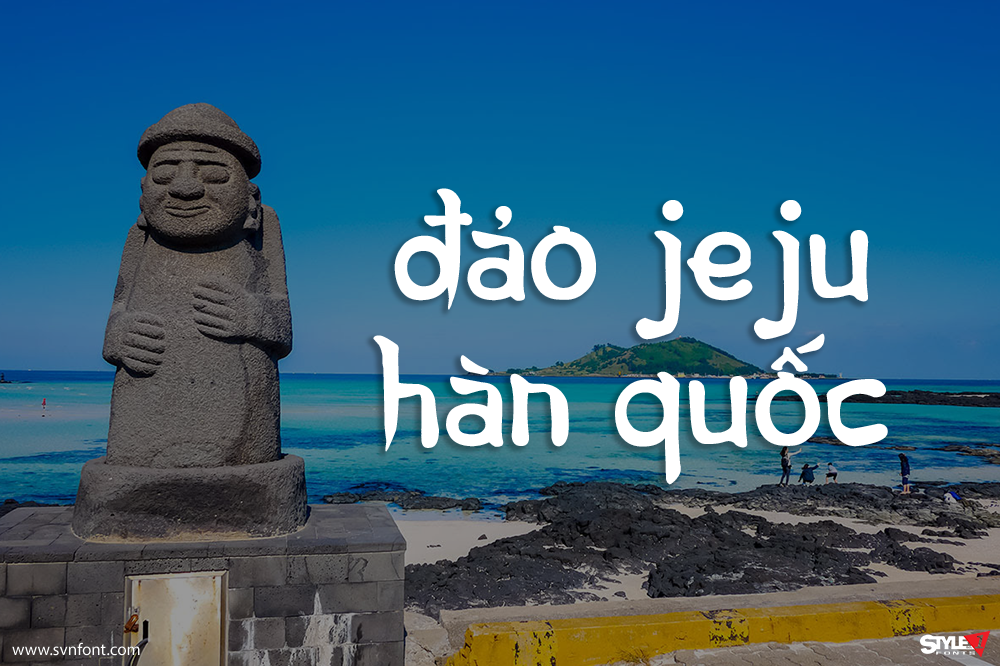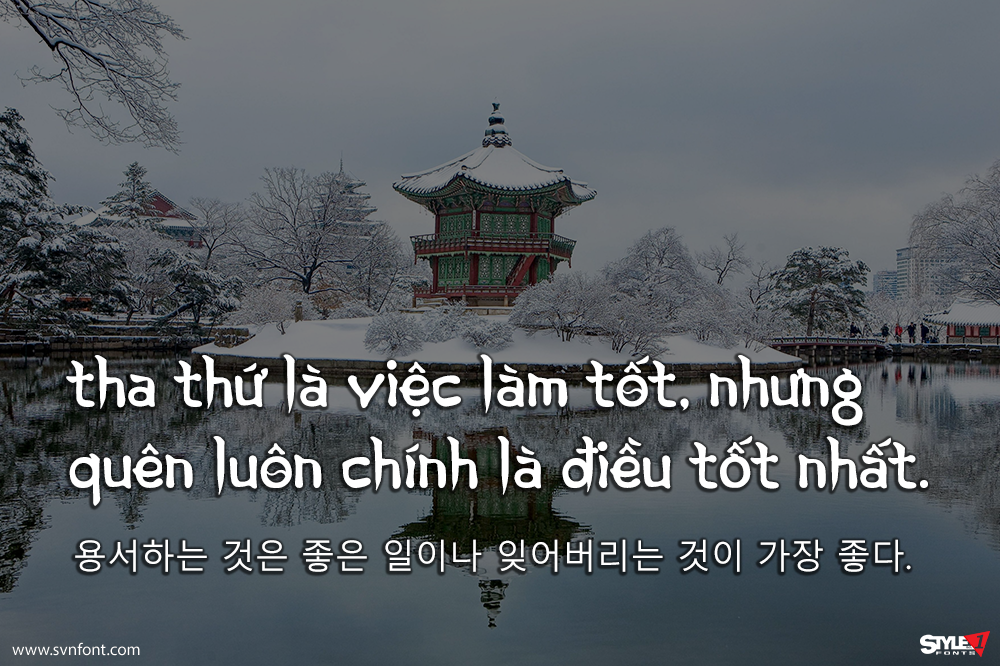
Korean Calligraphy Font được xây dựng dựa trên Hangeul – bảng chữ cái tiếng Hàn, phản ánh rõ tinh thần thư pháp truyền thống. Font đặc biệt phù hợp nếu bạn muốn tạo không khí phương Đông cho các dự án thiết kế, mang lại cảm giác văn hóa và nghệ thuật Á Đông rõ nét.
Một số ký tự không có sẵn cho font này: @ * # $ % ( ) & …